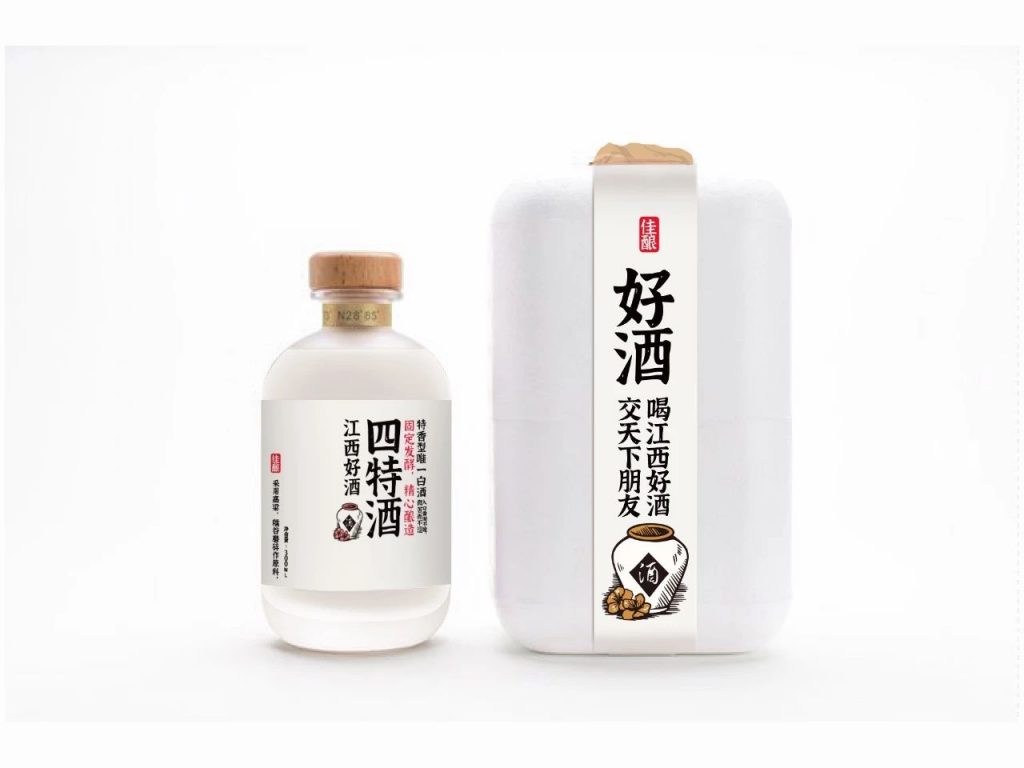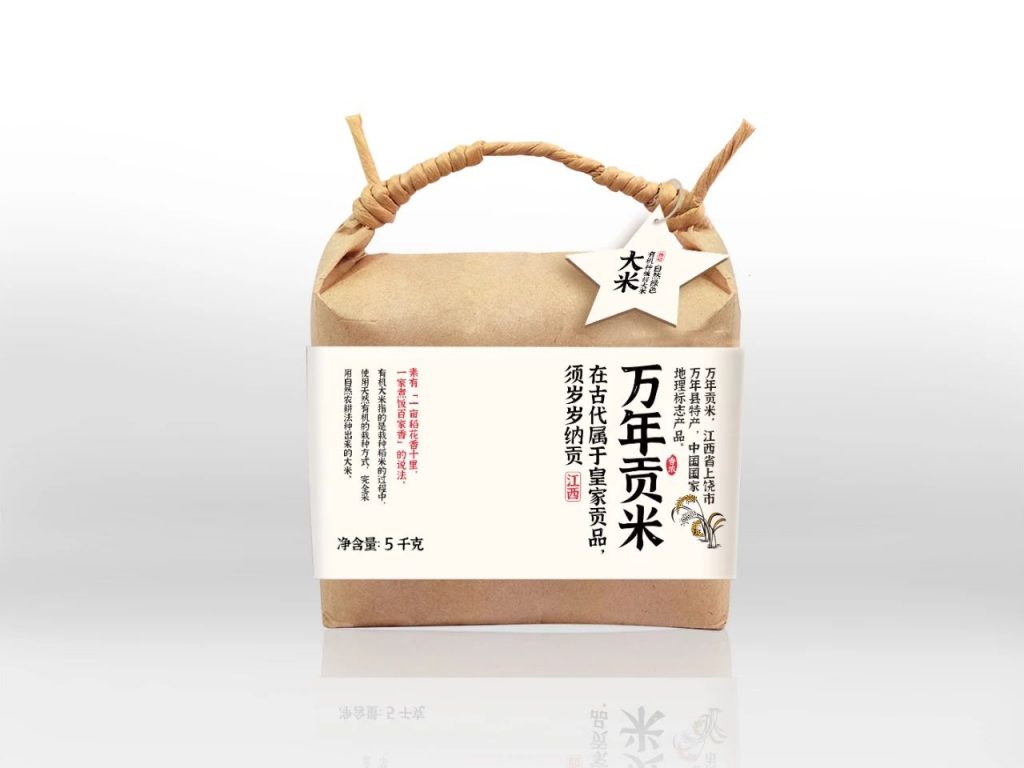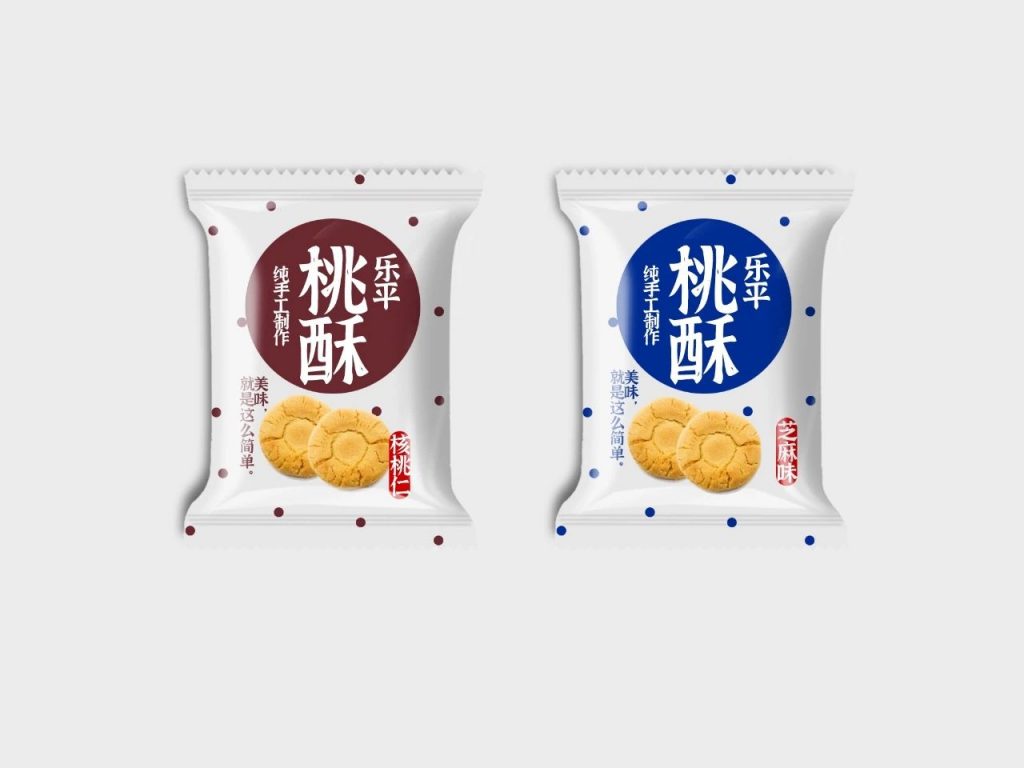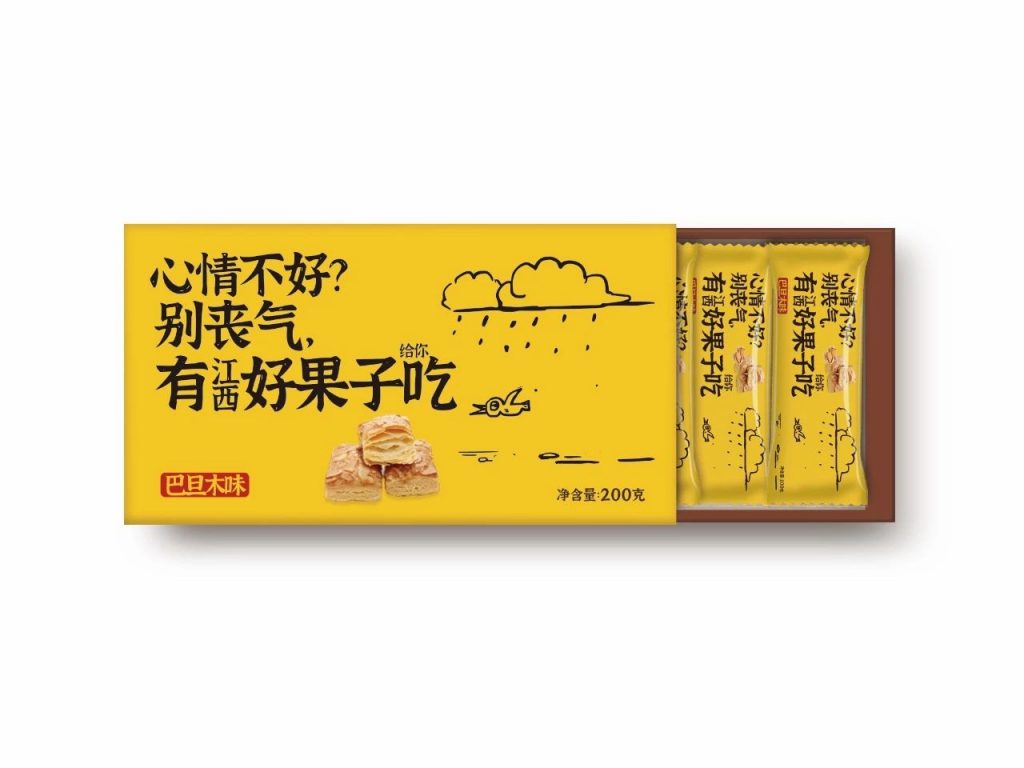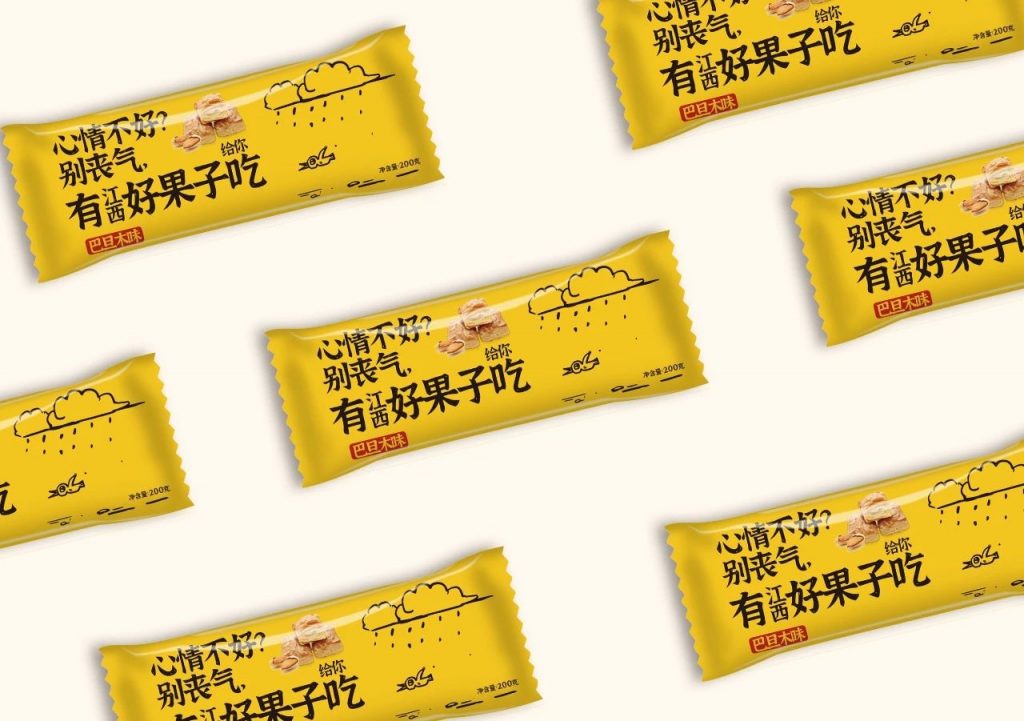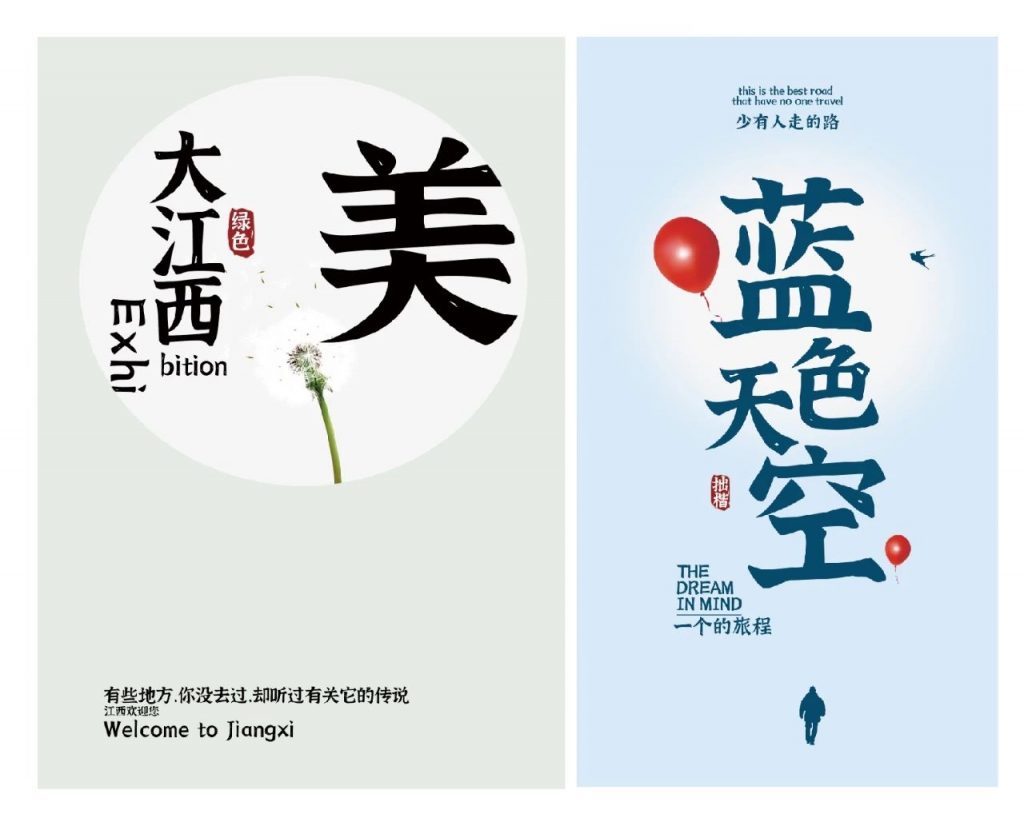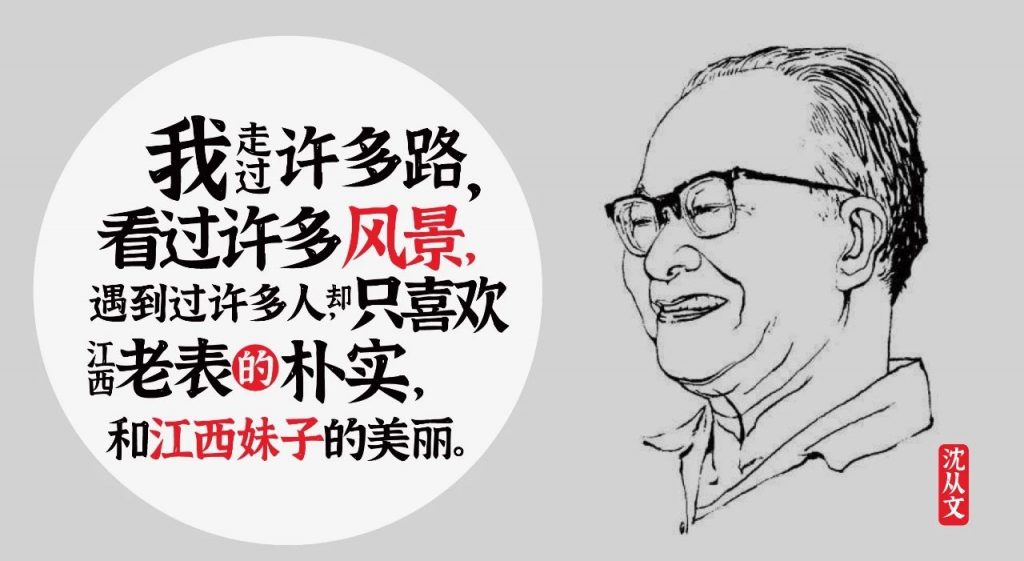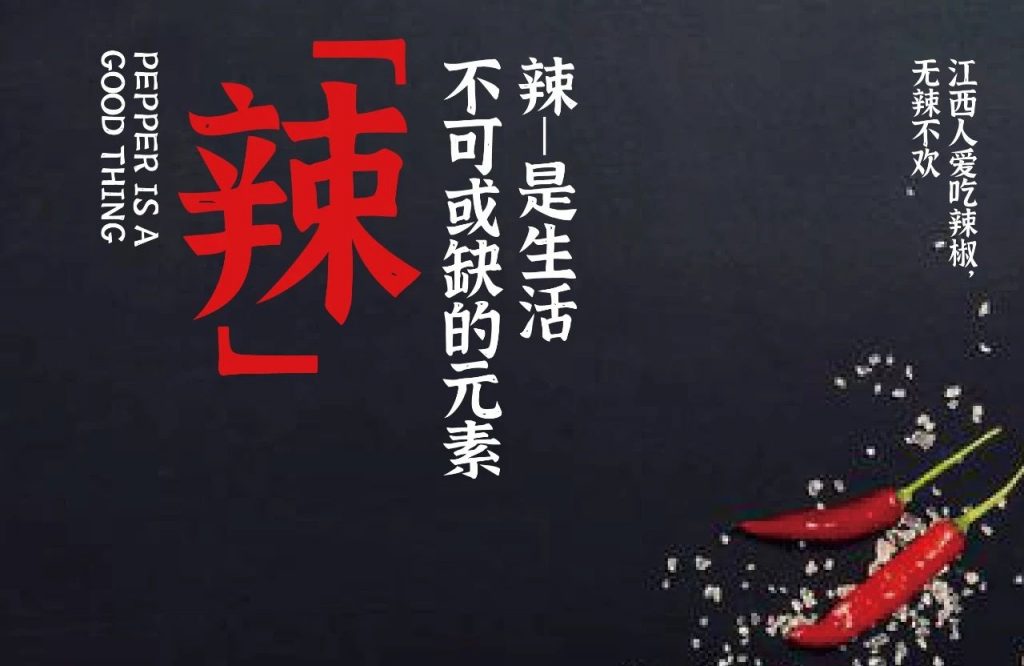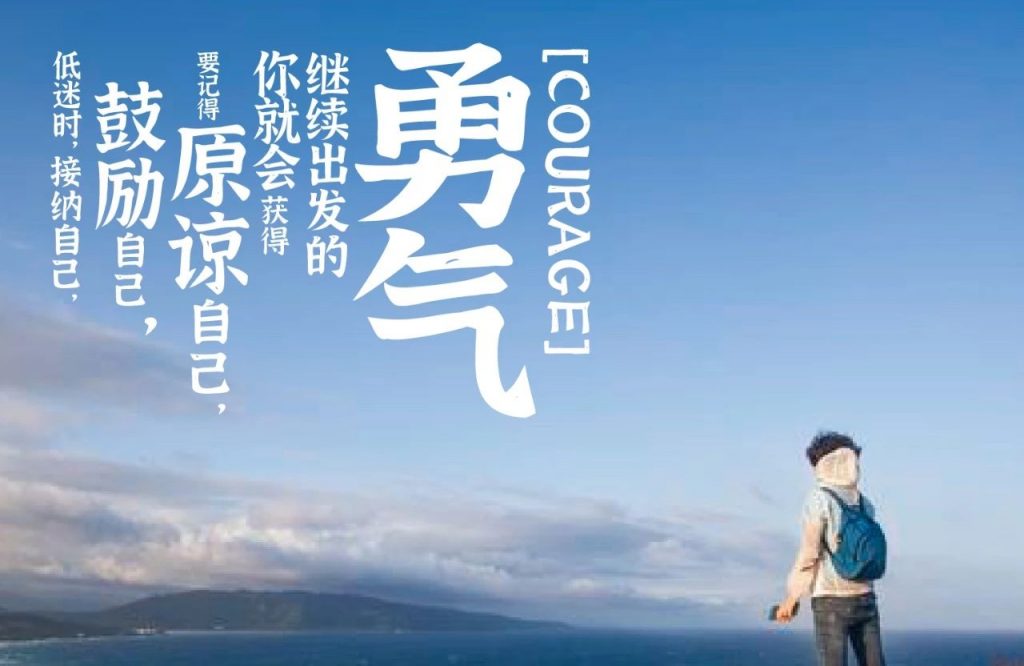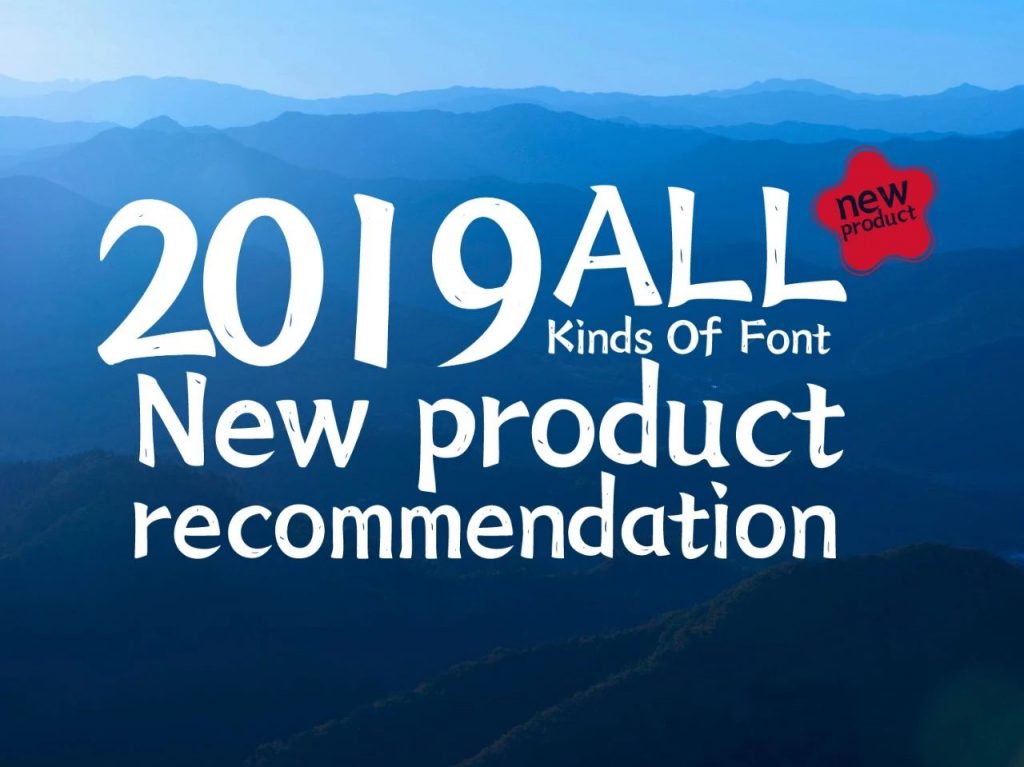
江西拙楷体:拙朴自然有趣味方显字体本色 精美免费商用楷体
字体作者:黄煜臣 (中国大陆) 字体字重:1个
2020年元旦,我们迎来崭新的一年。在这个特别的时候,我国设计黄煜臣也发布了今年第一套可以免费商用的字体「江西拙楷体」。做一套字体所需要花费的精力和时间是十分巨大的,黄煜臣同学半年多来夜以继日地辛劳创作才使这套非常漂亮的字体面世。大家可以加一下黄煜臣同学的微信公众号“字体树”请他喝杯咖啡或者冰阔乐吧。
这是一套手写楷体,相比电脑中标准化制作的楷体,这套字体的笔画会带有一些书写的痕迹,每个字的笔画是没有统一标准的,所以看上去显得不够规范,但是会有一种手写的自然之感。
黄煜臣如是说:
大家好,我是黄煜臣,我个人第一套字体,今天正式跟大家见面了。第一套字体的发布我内心有点小激动还有些忐忑,自己花了那么大精力去做这件事,今天终于有了一个阶段性成果,我不知道发布后会有什么效果,大家是喜欢还是无感?会不会带着期待而来,失望而去?不过俗话说的好,丑媳妇终得见公婆,藏着掖着不敢露脸只会让自己更加被动,敢于正视不同眼光的评判才是勇敢者的做法,如果有人喜欢这个丑媳妇,那将是一个意外的惊喜。
这是一套手写楷体,相比电脑中标准化制作的楷体,这套字体的笔画会带有一些书写的痕迹,每个字的笔画是没有统一标准的,所以看上去显得不够规范,但是会有一种手写的自然之感。这套字体从写手稿开始到现在的最终成品,前前后后花了近半年时间,仅仅是调节点,就花了20多天,其中的滋味做过才知道。
对于这款字体的发布,我不希望仅仅就是一款字体的展示,我希望它能发挥更大的作用,带来一些其他的价值,为了达到这个目的我想了很久——最终决定用这款字体为我们大江西做宣传。江西在各省市一直是一种低调的存在,不管是经济发展还是对外传播都是比较滞后的,我作为江西人,现在还没有能力用真金白银去为家乡做贡献,但是我可以用我的一点专业技能来为江西打打广告,做做宣传,希望让更多人认识他,喜欢他。
上面就是我这次发布的新字体,这款字的性格和江西很像, 低调内敛,朴实无华毫不张扬,就命名为江西拙楷,希望通过这套字体让江西增加点曝光度,让更多人来了解江西。